Chia sẻ 6 font chữ ghép ảnh nghệ thuật sáng tạo, độc đáo nhất kèm link tải
Một bức ảnh có thu hút và ấn tượng hay không không chỉ phụ thuộc vào phong cảnh và màu sắc của ảnh, nó còn dựa vào sự đặc biệt và phù hợp của Font chữ ghép ảnh với bức ảnh đó. Vì vậy bạn nên lựa chọn kiểu Font chữ sao cho tương thích nhất với tấm ảnh của mình để tăng hiệu quả thu hút của tấm ảnh nhé.
Giới thiệu về Font chữ ghép ảnh
Font chữ ghép ảnh thường là những Font chữ uốn lượn, độc đáo được chèn vào những bức ảnh để tăng độ nổi bật của bức ảnh đó. Các Font chữ ghép ảnh được sử dụng phổ biến cho nhiều chủ đề ảnh khác nhau, tuy nhiên chúng không có sẵn trong những Font chữ mẫu thường dùng hằng ngày. Vì vậy, nhiều người phải đi tìm kiếm các Font chữ ghép ảnh phù hợp trên mạng internet và tải về để sử dụng.
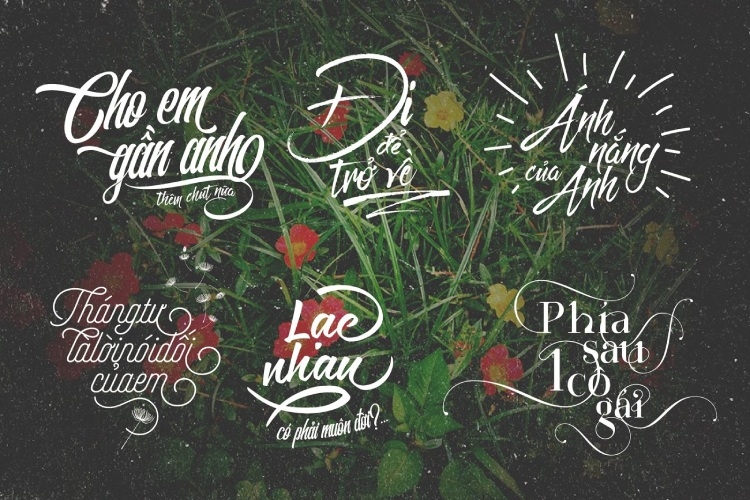
Thuật ngữ Typography là gì?
Typography là thuật ngữ nói về nghệ thuật sáng tạo, sắp xếp hình dáng câu chữ sao cho đẹp, mới lạ và thể hiện được tính thẩm mỹ cao. Nó thường bao gồm thiết kế về cỡ chữ, phong cách, kiểu chữ, độ giãn cách,… Thông thường Typography được dùng trong việc thiết kế các dự án hay tài liệu phục vụ cho học tập và công việc.
Một số Designer đã nhận định rằng những người có thể sử dụng Typography một cách chất lượng và hiệu quả đều là những người thật sự có nhiều kiến thức và kinh nghiệm làm việc liên quan đến mảng thiết kế. Nhưng thực tế lại không hoàn toàn như vậy, điều quan trọng nhất để dùng Typography hiệu quả là bạn cần nắm được lý thuyết và có gu thẩm mỹ sáng tạo, độc đáo.
Các bộ Font chữ ghép ảnh ấn tượng mới nhất
Hiện tại các Font chữ ghép ảnh khá phổ biến và đang có rất nhiều mẫu chữ cực đẹp cho bạn tha hồ lựa chọn. Tuy nhiên hãy lựa chọn kỹ càng Font chữ phù hợp nhất với bức ảnh của bạn, nếu không thì chính Font chữ đó sẽ khiến bức ảnh trở nên kém thu hút hẳn đi đấy.
Bộ Font chữ “Thanh Xuân”
Dưới đây là bộ Font chữ ghép ảnh chủ đề Thanh Xuân siêu đẹp để bạn có thể ghép vào bức ảnh của mình. Những Font chữ này có định dạng PSD, vì vậy bạn có thể ghép vào nhiều kiểu ảnh như ảnh kỷ yếu, ảnh du lịch,…
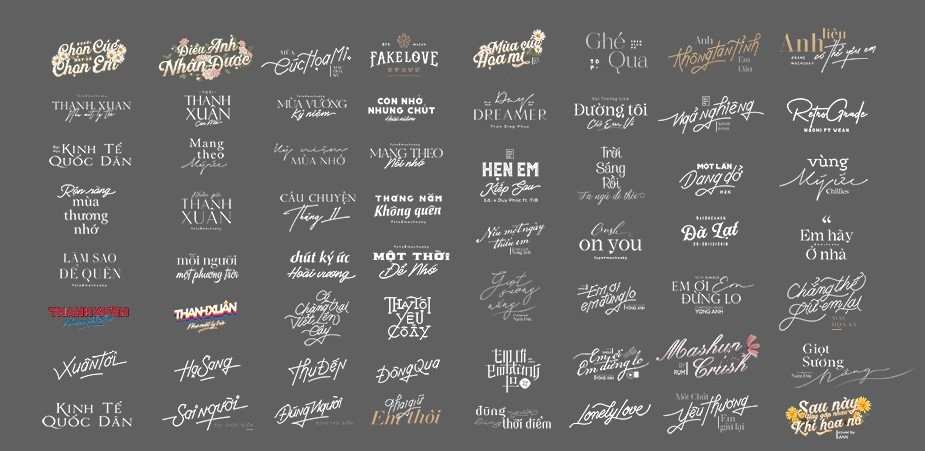
Bộ Font chữ “Chỉ còn là hồi ức”
Những Font chữ trong bộ Font này gây ấn tượng nhờ đường nét uốn lượn nhưng vẫn rõ ràng và không gây rối mắt. Nếu bạn vừa chụp được một bộ ảnh hồi ức, retro mà muốn ghép thêm chữ vào cho sinh động thì đừng bỏ lỡ bộ Font chữ này nhé.
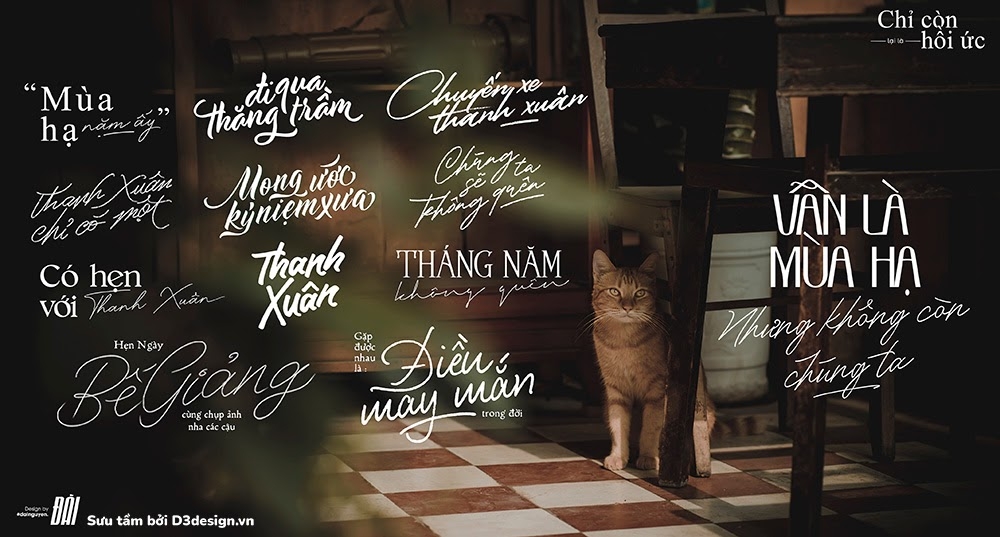
Bộ Font Calligraphy Trung Quốc
Font chữ Calligraphy Trung Quốc thích hợp dùng để chèn vào những tấm ảnh sâu lắng mang hơi hướng Trung Hoa. Trong bảng Font chữ này còn có một số ký tự Latin và chúng đều được Việt Hoá cho bạn dễ dàng sử dụng hơn.
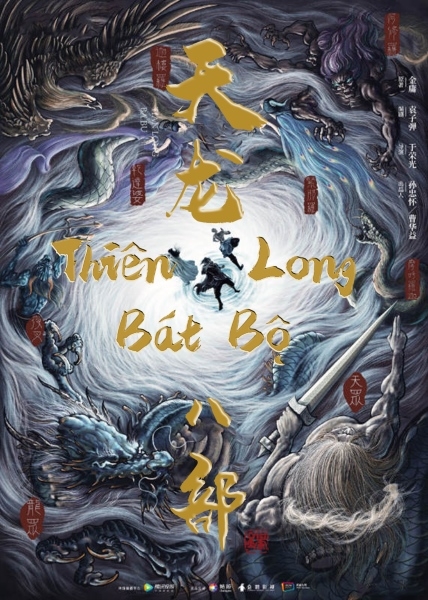
Bộ Font chữ “Đại Tự Lão Trọc”
Đây là bộ Font chữ thư pháp đại tự nét xước được mô phỏng lại dựa trên nét thư pháp cực ấn tượng của Lão Trọc.
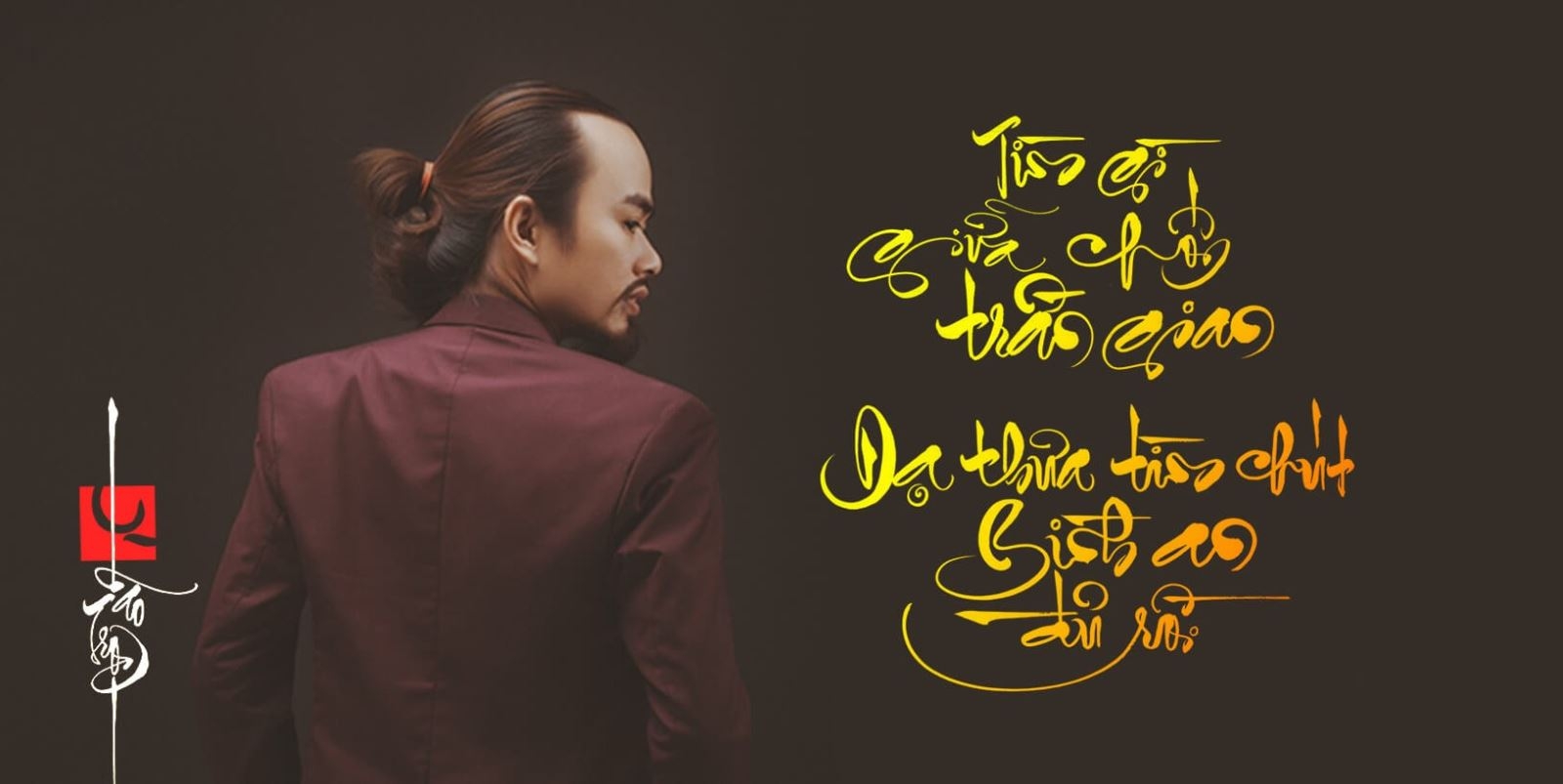
Bộ Font chữ với phong cách Sài Gòn xưa
Với những nét chữ vừa cứng rắn nhưng vẫn có sự mềm mại tạo nên nét đặc sắc riêng, Font chữ này sẽ giúp cho bức ảnh của bạn trở nên vô cùng thơ mộng và cổ điển. Những chữ cái được phác họa bằng những đường cong uốn lượn tự do không theo một quy tắc nào có thể tạo ra được sự nhẹ nhàng, hài hoà.
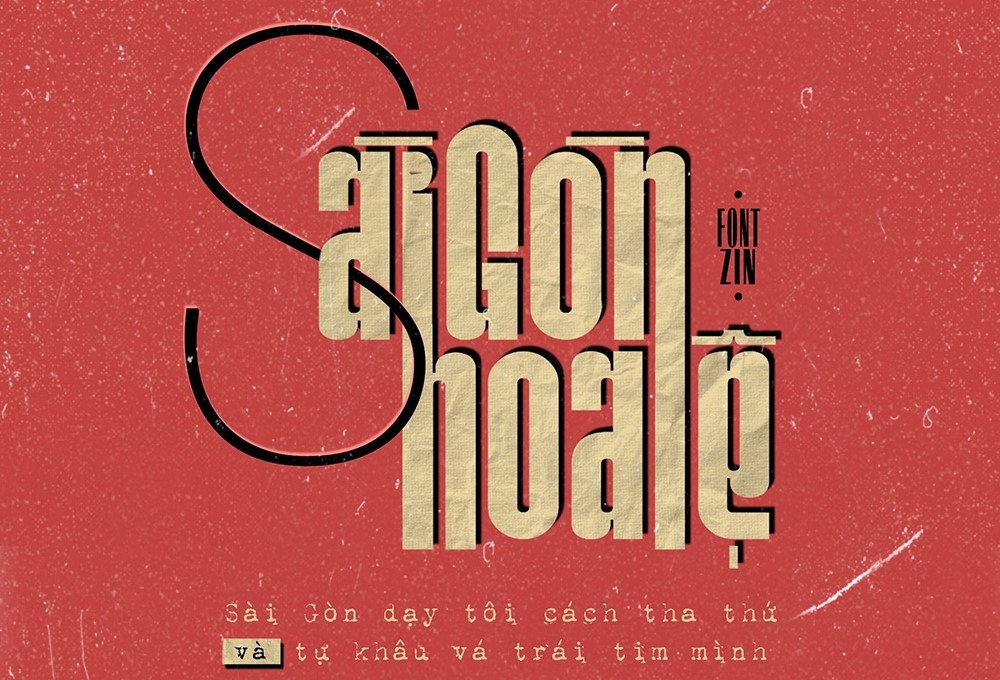
Bộ Font chữ SCRIPT and HANDWRITTEN
Bộ Font chữ SCRIPT and HANDWRITTEN với đường nét thanh mảnh, nhẹ nhàng và bay bổng, mang lại cảm giác thanh lịch và lãng mạn cho bức ảnh của bạn.